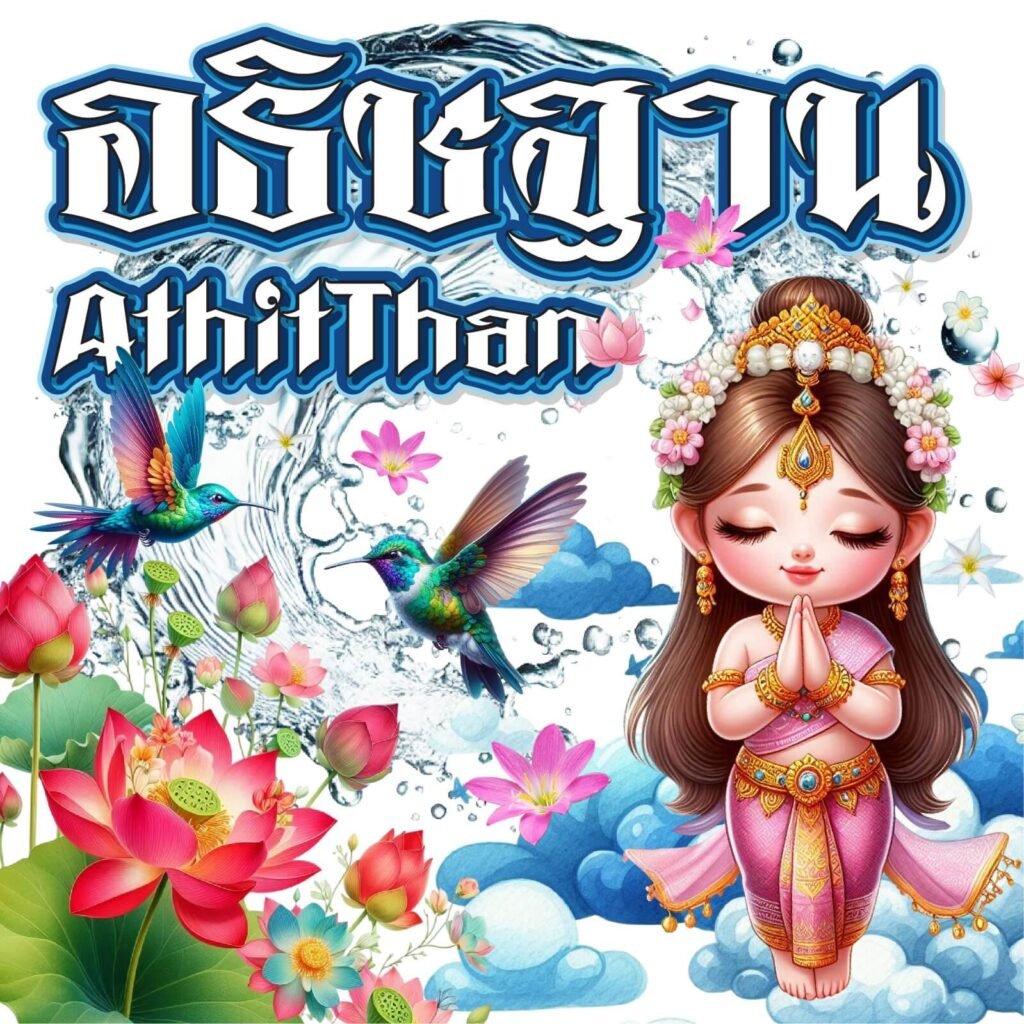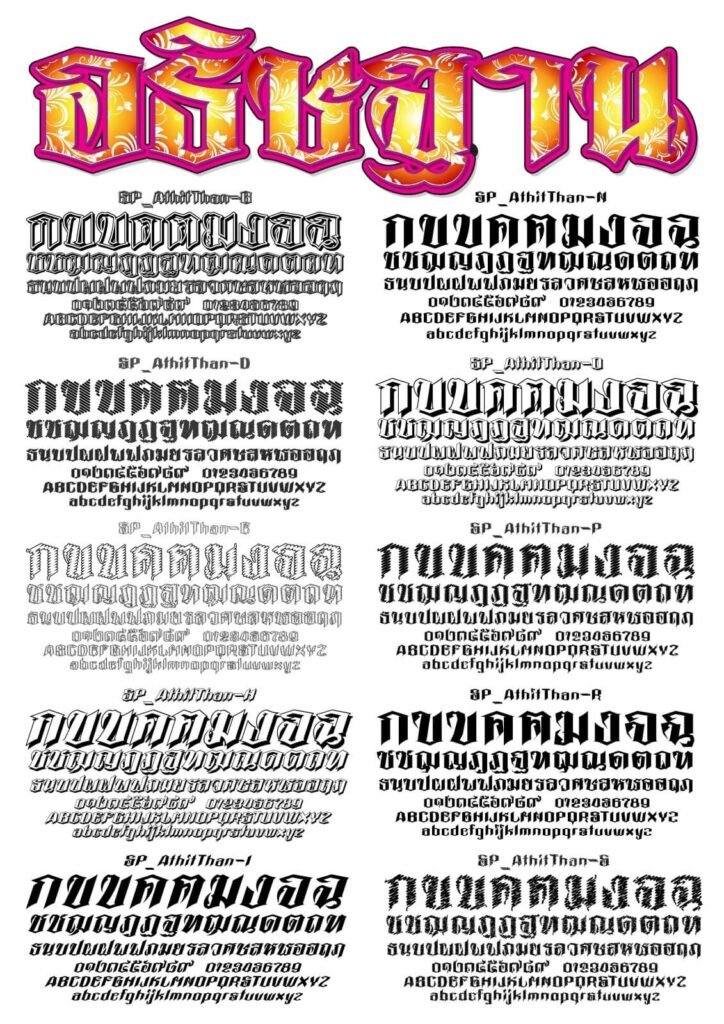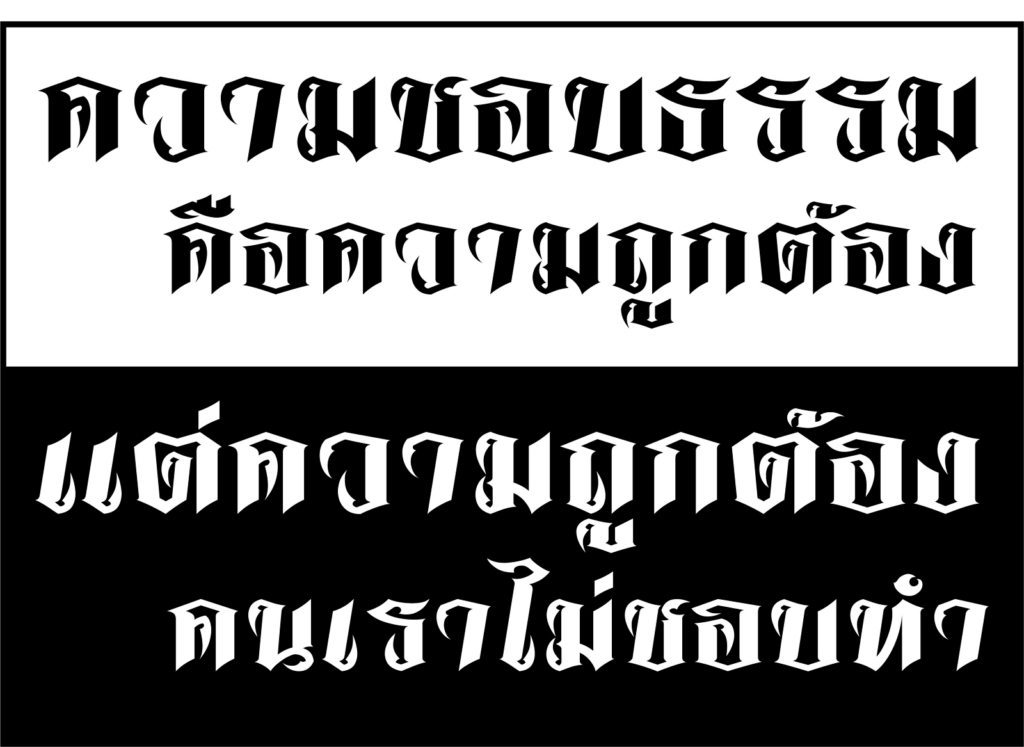
อธิษฐาน (SP_AthitThan)
อธิษฐานฟอนต์ ฟอนต์ไทยวิจิตรศิลป์ ที่ออกแบบมาให้ดูปราดเปรียว เฉี่ยวคม มาพร้อมกับเอฟเฟกต์สไตล์ รวม 10 รูปแบบ
ฟอนต์อธิษฐาน พร้อมให้ท่านได้อธิษฐานแล้วในดวงจิต